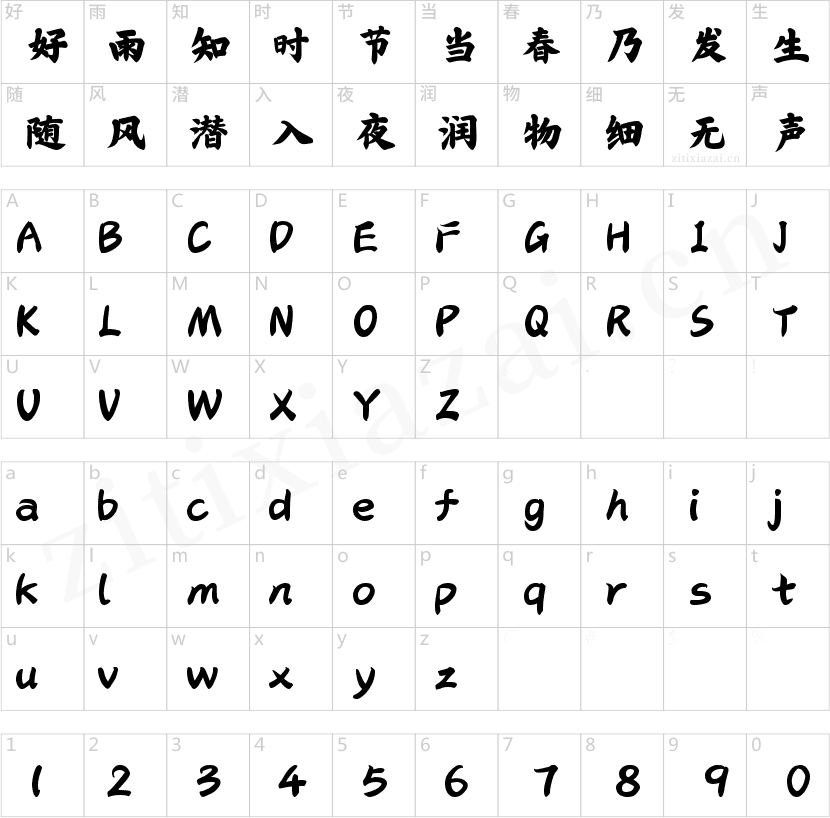
字魂龙行龘龘体
字魂龙行龘龘体,这款字体结构工整、笔画清晰,兼顾美观与易读性,适用于标题、正文、海报、包装、LOGO 等多种场景。字形优雅稳定,风格百搭耐看,适配日常排版与创意设计,让文字呈现更舒适、更具质感。字魂龙行龘龘体一笔一画,皆是细节,以均衡的比例、流畅的线条打造舒适视觉体验,字形端正大气,风格简约现代。无论是商业设计、品牌宣传还是日常排版,都能轻松驾驭,让文字更有格调与力量。字魂龙行龘龘体字体下载。